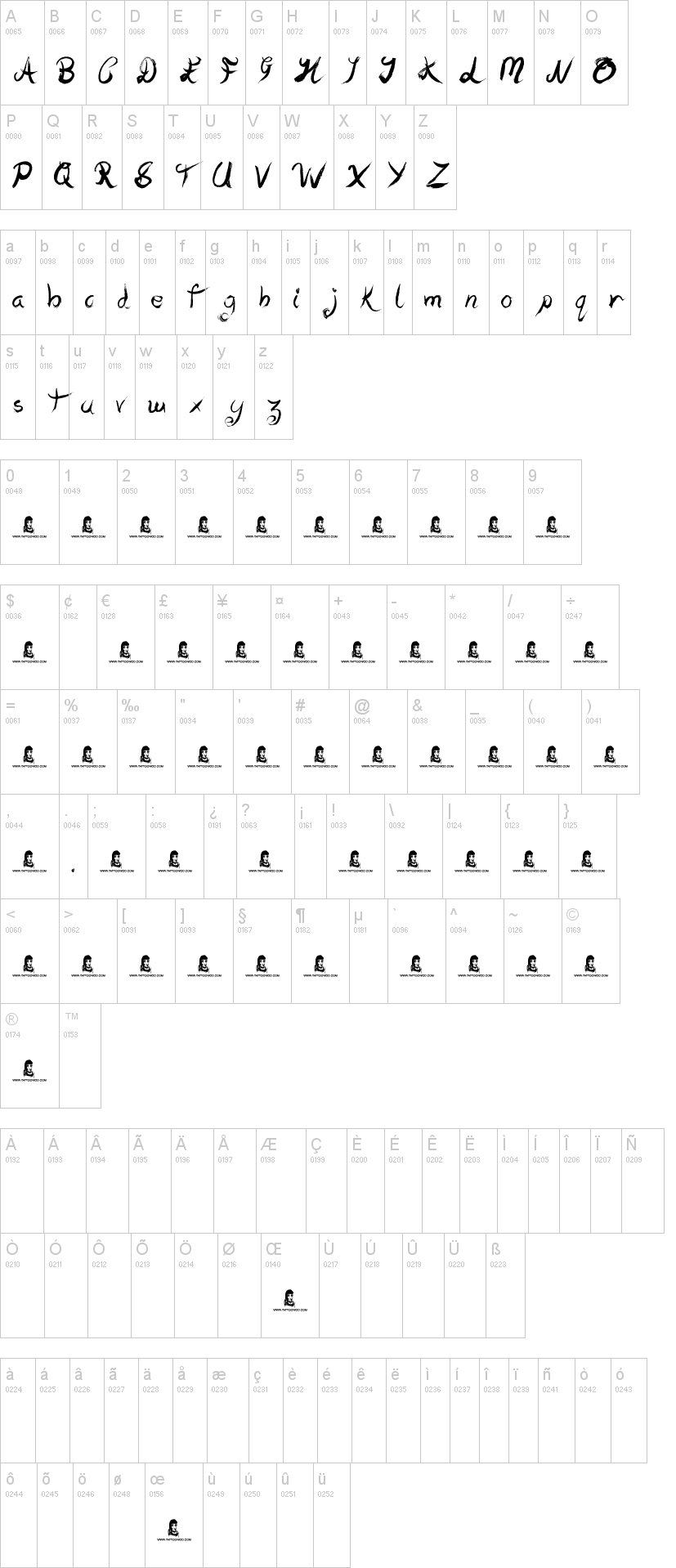
Texas是一种类似手写的无衬线字体,由美国设计师Charles Nix创建。它的特点包括宽松的字距、圆滑的笔画和斜角的末尾。Texas字体被设计用于印刷和数字应用程序,并且非常适合用于包装、标志、广告、海报等各种设计项目。该字体有多种字重和风格可供选择,包括正常、斜体、粗体和粗斜体等。Texas字体的设计意图是为了展现出德州州的时尚和活力。内容介绍
Texas是一款非常不错的手写艺术字体,具有很好的视觉感,适合于文化类的宣传设计、商业类品牌的广告和产品包装设计以及个性化文字排版等较多场景。